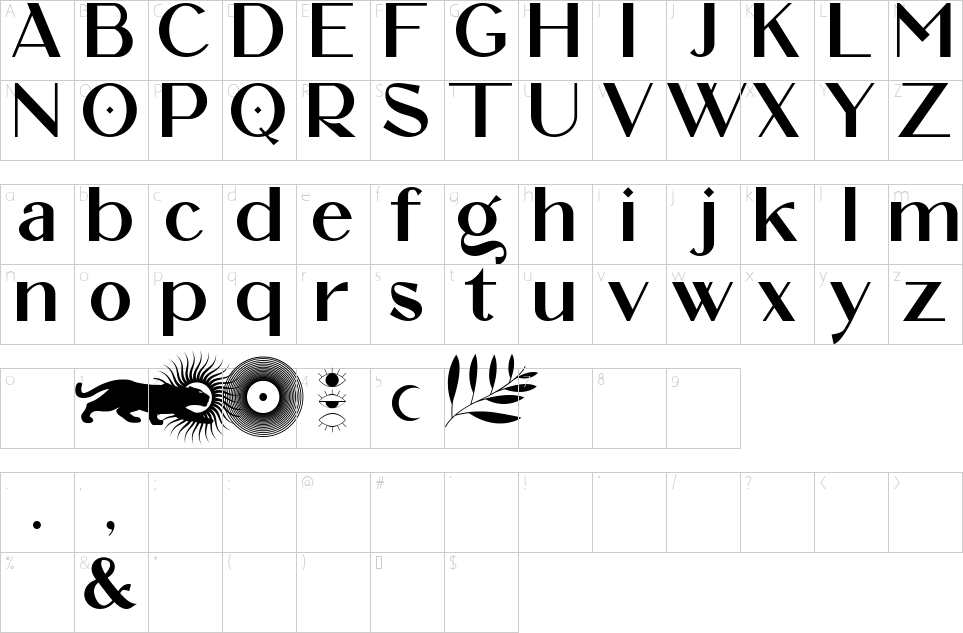
A fonte Marde Sauve é uma escolha ótima para aqueles que buscam uma fonte moderna e elegante. Desenvolvida por Putu Dody Permana, ela se destacou pela sua simplicidade e sofisticação, tornando-se uma opção popular para designers gráficos. As fontes são essenciais para qualquer projeto digital, seja para criação de logomarcas, postagem em redes sociais ou simplesmente para escrever artigos de notícias. Para aqueles que buscam um estilo clean e sofisticado, Marde Sauve pode ser a fonte perfeita para incorporar em seus projetos. Esta fonte foi descarregada 312 vezes, demonstrando seu valor e popularidade entre os designers brasileiros e internacionais. Descubra por si mesmo o poder desta fonte única e elegante.